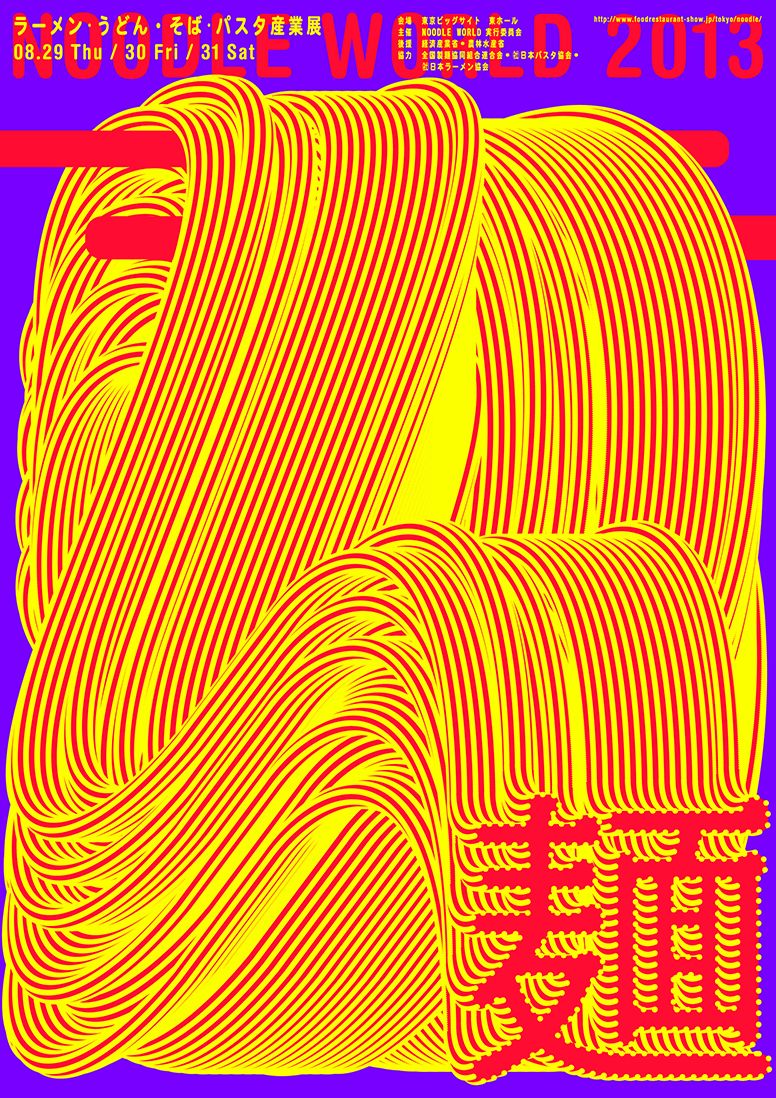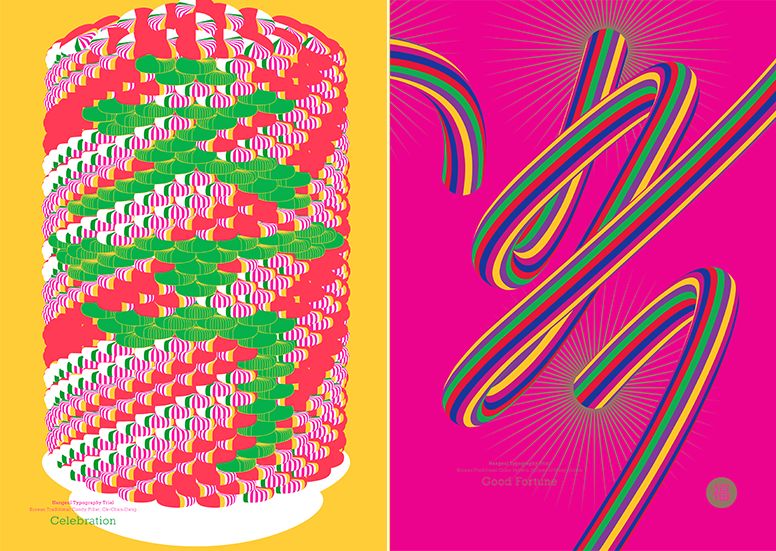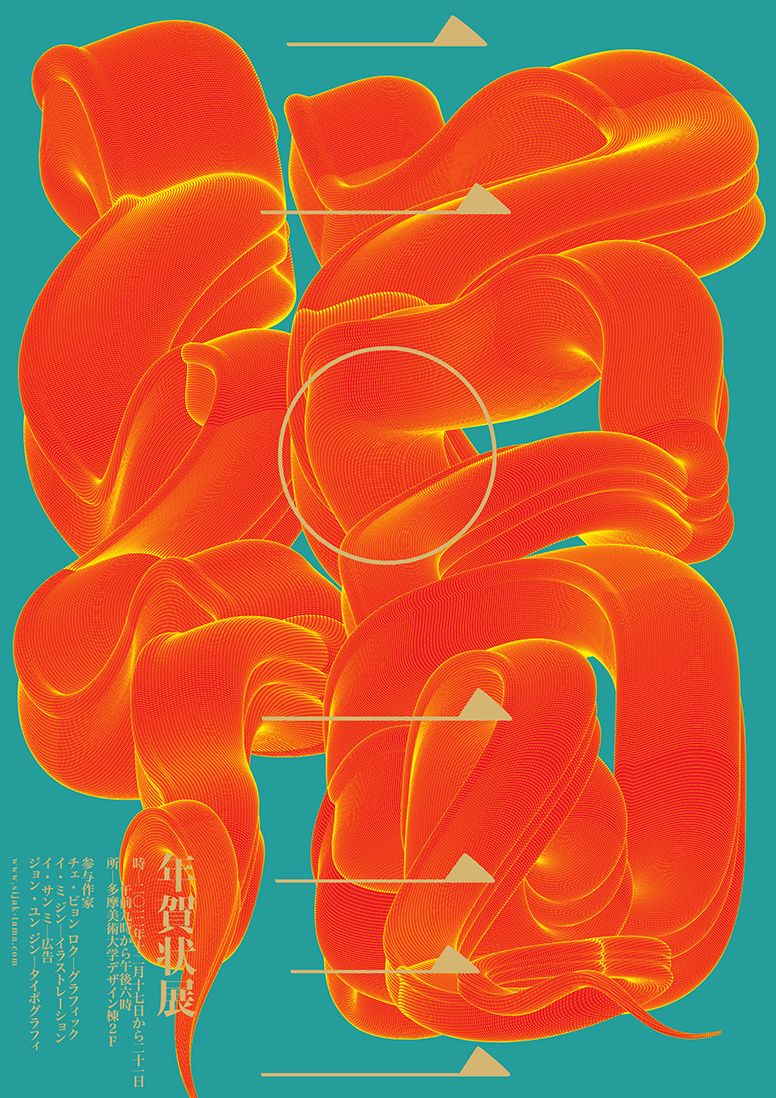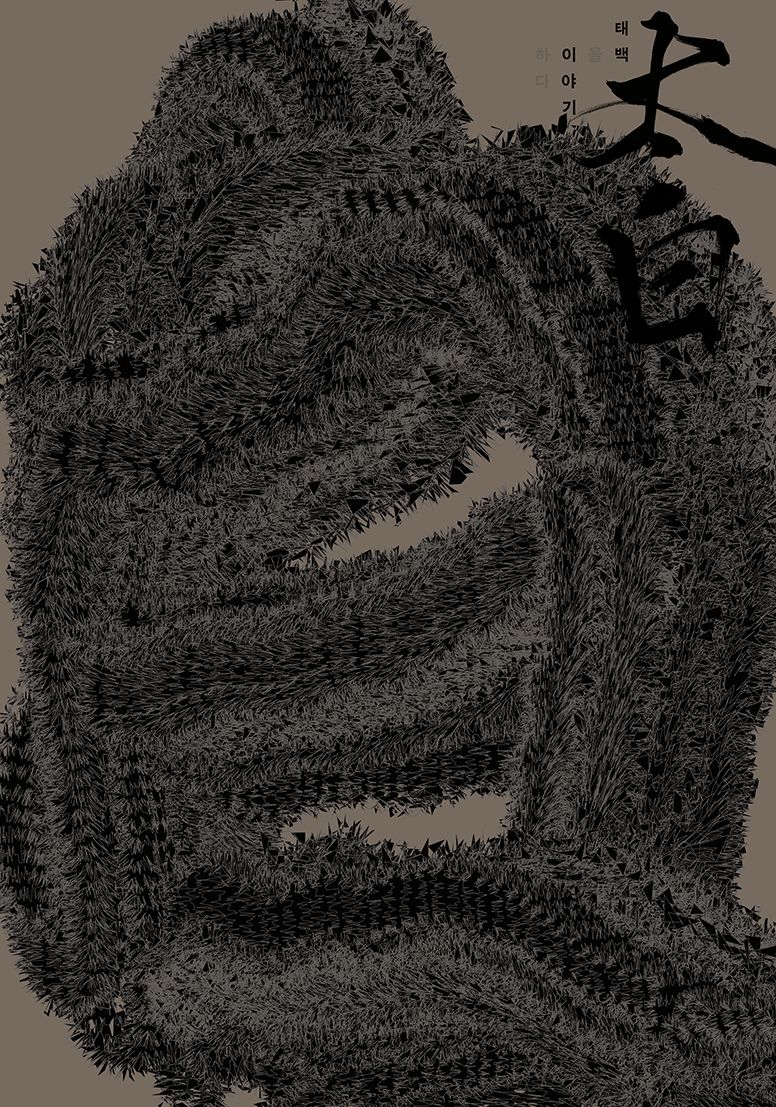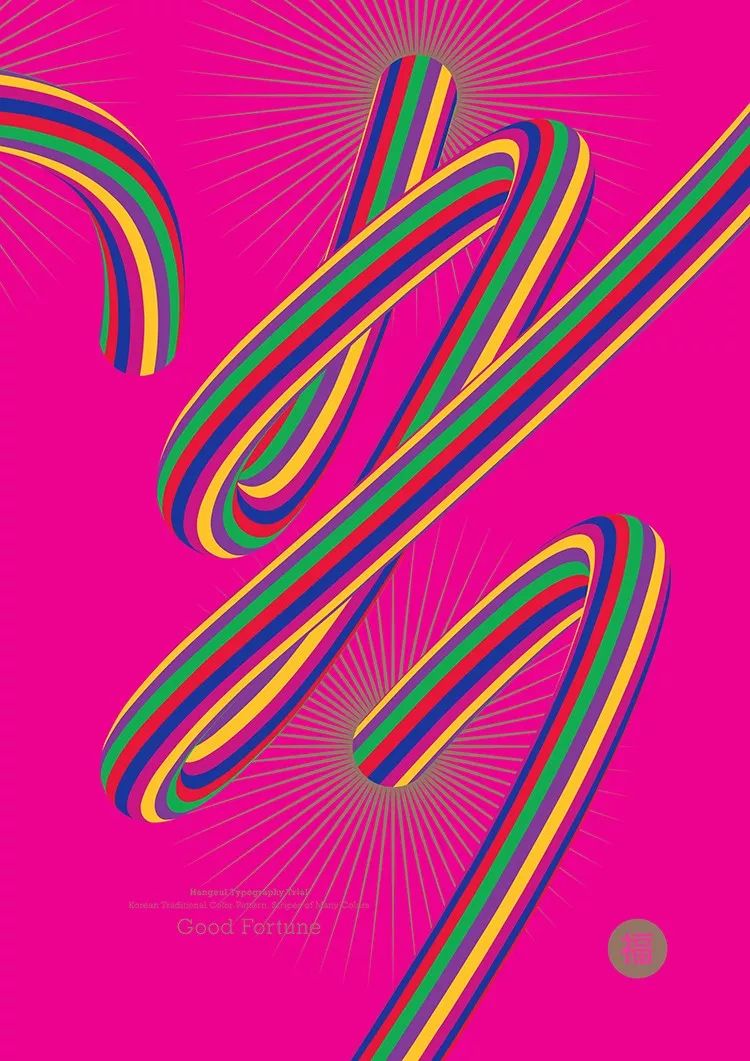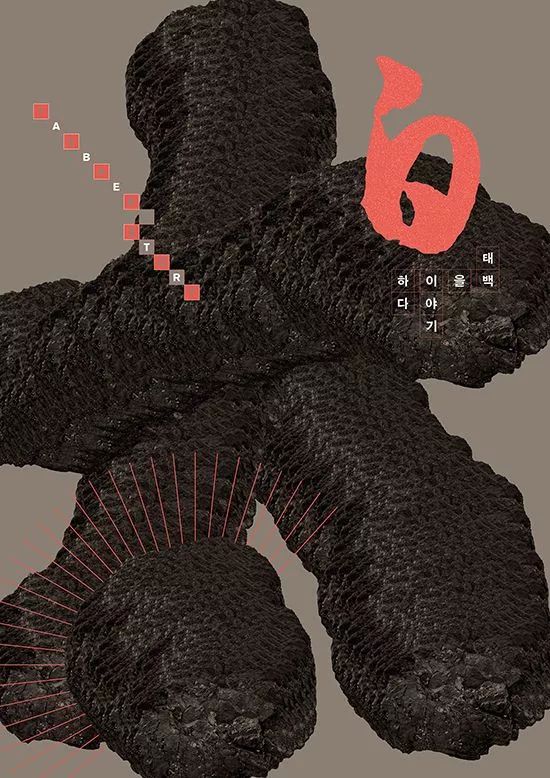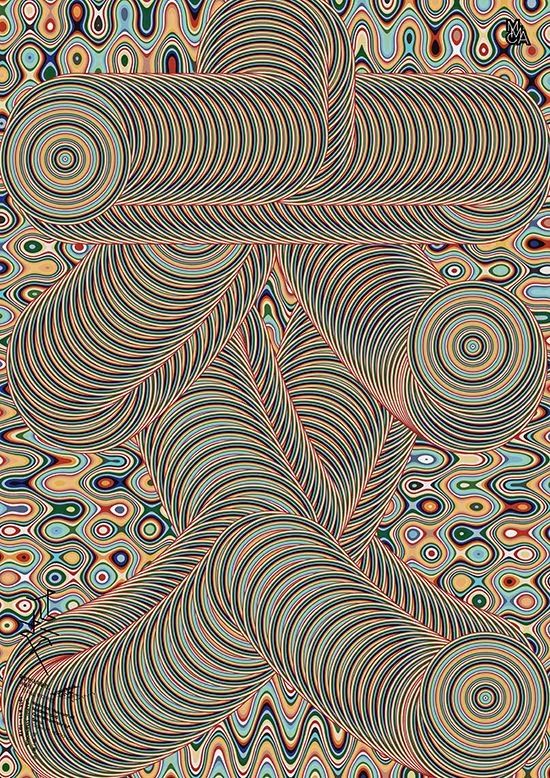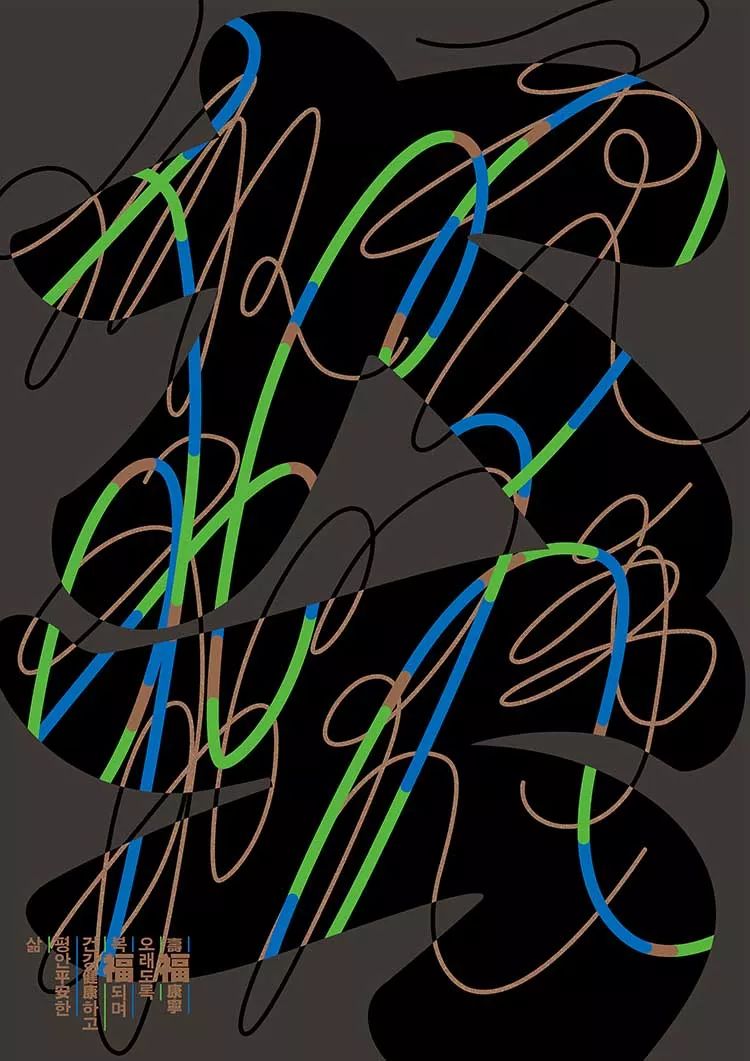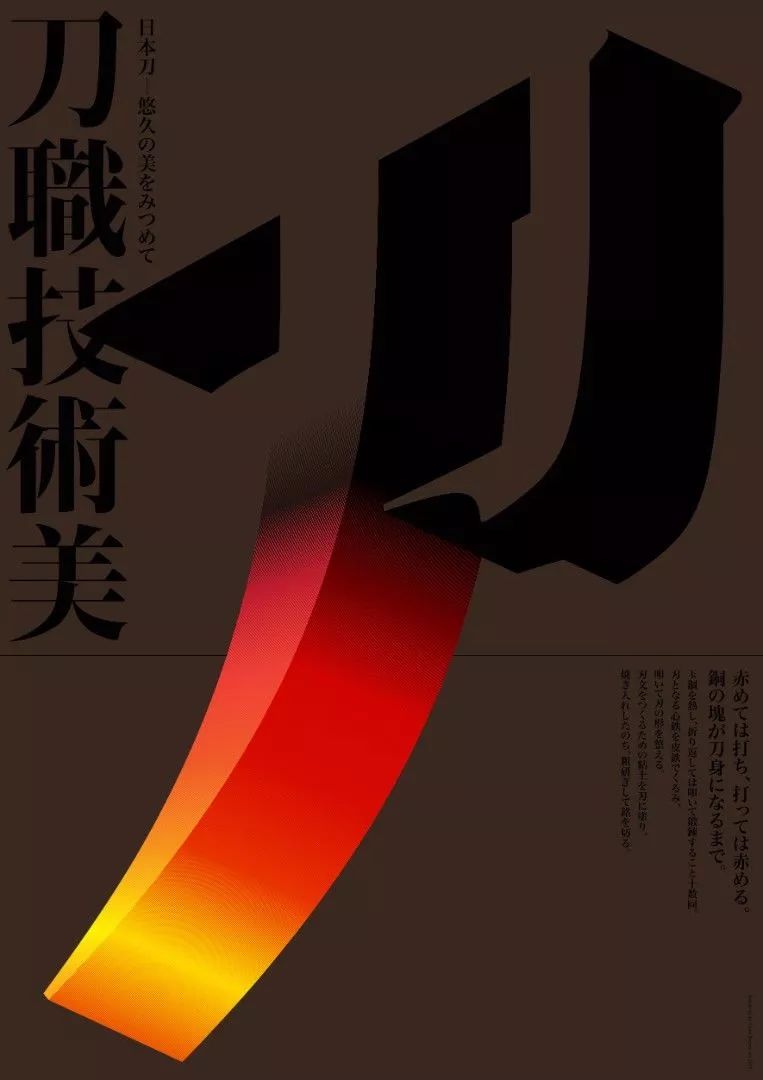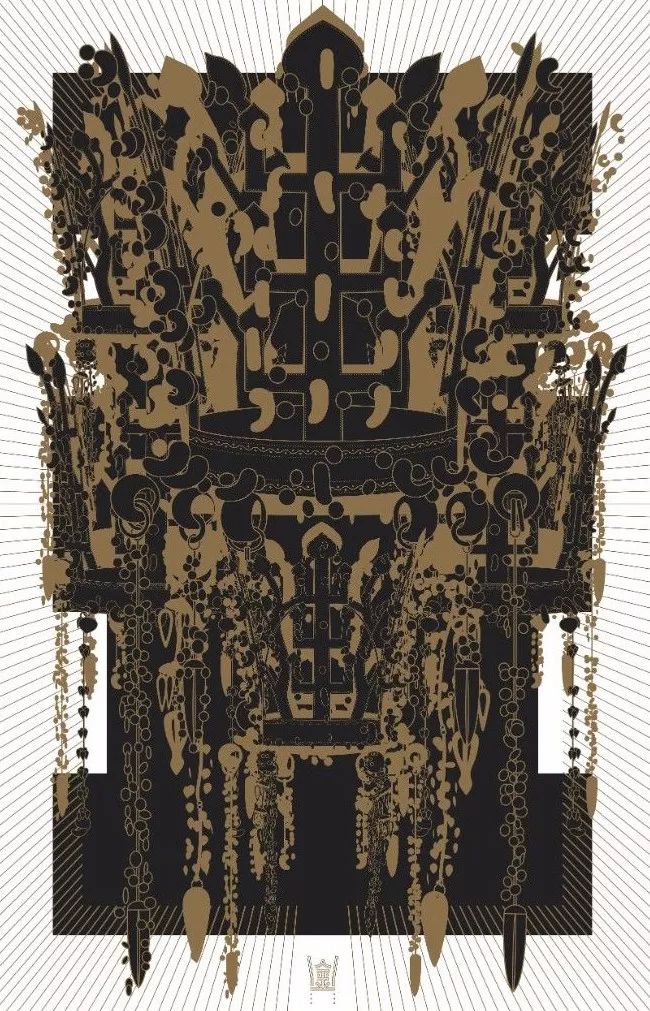
这位韩国的设计师,喜欢用字来塑形
Chae Byung-Rok
채병록
by Korea
韩国CBR设计工作室 艺术总监
蔡炳禄(Chae Byung-Rok)韩国平面设计师,生活工作于首尔。曾在日本多摩艺术大学佐藤晃一(Koichi Sato)的指导下研习平面设计,之后建立了自己的工作室CBR Graphic。
他的作品在视觉语言表现上极为丰富生动,注重以概念来表达设计。擅长用字体作不同的图形表现、抽象以及各种技术上的混合应用。这种极具韩式感的东方式设计风格,使他的海报更具有独特的感染力和吸引力。
海报做为平面视觉传达中独立存在的媒介形态。从图像到文字,所有的视觉元素都能在一张画面上表现出来。而视觉传达的基本功能,就是要快速有效的将信息传递出去。在Chae Byung-Rok的平面设计中,利用文字为介质的表达形式不单只是在表现汉文字的美;而是作为一种简洁的图形,为海报所用。海报不仅是传达信息的媒介,同时它也是代表内容的一个标签。海报中不仅要有设计师自己的思想,而且还要传达给观众让其产生共鸣感。
Chae Byung-Rok对海报有着浓厚的兴趣,热忠于实验性海报的设计。他通常会在生活或周围事物当中汲取灵感。寻找一些日常中的自然形态,并去思考。就好像我们电脑卡机时拖动文件,它就会发生反复重叠的图像效果,如果可能,就把文字以这种图像的形式将其表现出来。简单的字体与电脑卡机时所产生的错觉图形,经常是Chae Byung-Rok日常设计时的灵感启发。
面条世界Noodle World 2013是日本(麺)博览会的海报,也是Chae Byung-Rok最喜欢的一件作品,它优雅地展示了面条从静止的筷子上飘落下来的画面。
这些年来Chae Byung-Rok一直为展览和自创项目而设计。还经常与各种文化组织以及公司合作。此外,他还在大学教授印刷术和图形表达。
2013年新年贺卡展览主题海报。癸巳年,以蛇形刻画出来的“福”字
2014庆典海报,米粉糖中加入多种颜色制成的传统玉春糖,用韩文字体来表达作品的意境。
将韩国传统宴会桌上摆放的高级食物形态,制作成一种重复和堆积起来的结构。
好运2014,以韩国传统色彩—彩动(stripes of many colors,带有许多条纹的颜色)来充分展现了韩字“복(福)”的节奏及韵动感。
太白的故事海报 2014
太白的故事海报 2015
2015庆典海报, 以福寿康宁与仰天祝寿的意义,交于两幅海报中。
将作家对祝福的思考表现在图形上。
福贺卡2016,丙申年即12生肖中的猴年,通过以汉字“福”字与猴图形的结合让整个画面更加生动有趣。
2012年刀職技術展,日本刀的生成过程和形态,
以及把陶瓷匠的匠人精神用刀的文字表达出来的作品。
这是2013年东亚的设计师们齐聚一堂,探讨东方思想与美学的研讨会海报。从东方审美意识的角度出发,通过毛笔刻画主题的作品。(毛笔是东方人文及美学的一种象征)
2012韩国抽象造形展海报,以字体"形'为主要表现载体,对其进行夸张有形式感的表达,
很好的传达出造形展的立意。
吉祥寺设计节2012
交·响 — 图形交响乐2015
2012日本传统工艺展
2013日本道具展,用“束”字来表现日本的日常生活必需品。
束子即日本生活用品中的洗刷用具。
2012日本多摩艺术大学毕业展海报
韩国KCDF国立博物馆-产品周边图形设计
还有Chae Byung-Rok以中秋“满月万福”为主题的海报设计。以东方美学的方式呈现万月的形态,将其视觉化。通过圆头饭、苹果、梨、柿饼等中秋食品、玉春糖、西瓜果冻等高级食品,表现出和谐与丰富的元素。
梨,苹果Pears and Appples 2017
一碗满满的米饭 A Full Bowl of Rice, 2017
月亮、老虎和柿子
满月万福
在未来Chae Byung-Rok会继续以极具韩式感的东方式设计手法。做不同的新的视觉实验,期待以后能看到更多Chae Byung-Rok的作品。